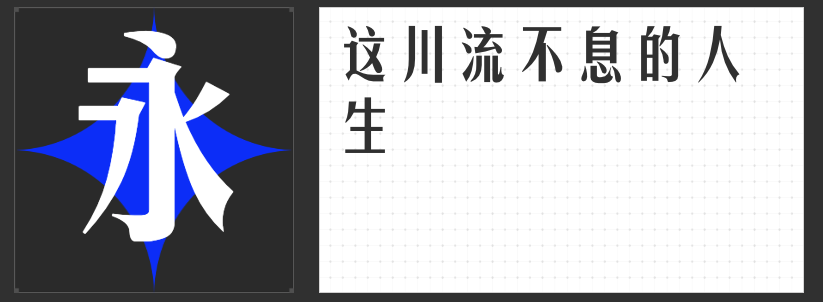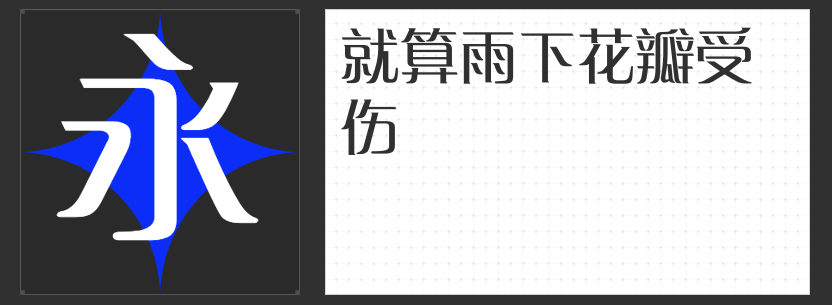
四款高适配性印刷字体美学解析
在印刷品追求视觉层次与艺术表达的今天,字体的选择直接影响信息传递的质感与温度。本文精选四款兼具功能性与艺术性的专业印刷字体,从结构创新到风格融合,为书籍装帧、包装设计、品牌视觉等领域提供多元解决方案。
一、励字综艺简繁
以“满版填充”为设计核心,励字综艺简繁通过加粗笔画与圆润拐角处理,构建出充满张力的视觉框架。其横竖笔画严格遵循几何比例,在保证阅读流畅性的同时,赋予文字雕塑般的立体感。字腔内部通过微调负空间,避免粗笔画带来的压抑感,尤其适合标题设计与信息层级突出的版面。圆弧过渡的设计语言,既保留了传统印刷体的严谨性,又通过柔和的视觉触点传递现代审美。
二、励字励倩简
基于扁平硬笔书写轨迹的再创造,励字励倩简以“微圆弧笔锋”为核心特征,将尖锐的棱角转化为温润的曲线。笔画粗细对比控制在黄金比例区间,既避免了单调感,又维持了字形的整体协调性。其方正饱满的字型结构,暗合传统印刷的“中宫收紧”原则,而婉转的笔画走势则赋予文字流动的韵律感。这种刚柔并济的设计语言,使字体在传达正式信息时仍保有亲和力。
三、励字志向黑简 超粗
针对数字印刷与屏幕显示的双重需求,励字志向黑简 超粗创新性融合圆体与黑体基因。通过在笔画拐角处植入适度外圆角,既消解了传统黑体的机械感,又强化了字体的结构稳定性。超粗笔画设计确保小字号下的清晰可读性,而充实的字面率则提升了版面的视觉重量。这种“稳中带活”的设计哲学,使其成为高端包装、户外广告等需要强视觉冲击场景的理想选择。
四、励字美黑简
励字美黑简突破性地将宋体笔意与黑体结构相结合,横细竖粗的经典比例被重新解构为匀称的现代美学。其笔画起收处保留宋体的装饰性,但通过简化衬线提升印刷适应性;中宫适度放开的设计,则赋予文字舒展的呼吸感。这种“端而不僵,正而不板”的视觉特质,使其在政府文件、学术著作等需要权威感的场景中表现卓越。
四款字体均通过专业印刷适配性测试,在胶印、数码打印等工艺中均能保持线条精度与墨色均匀度,为设计作品注入可持续的美学价值。